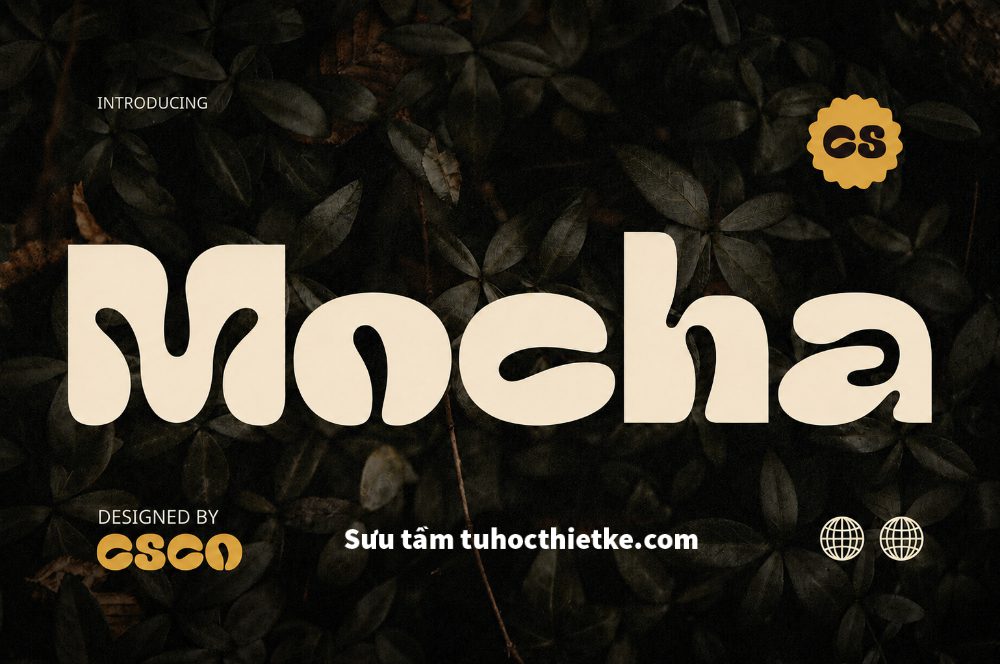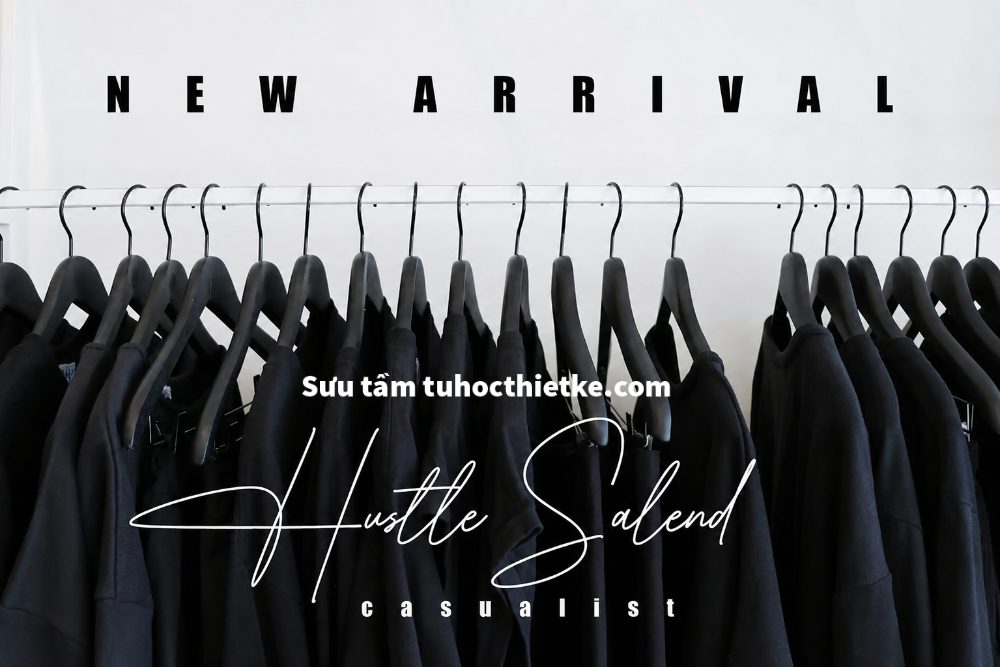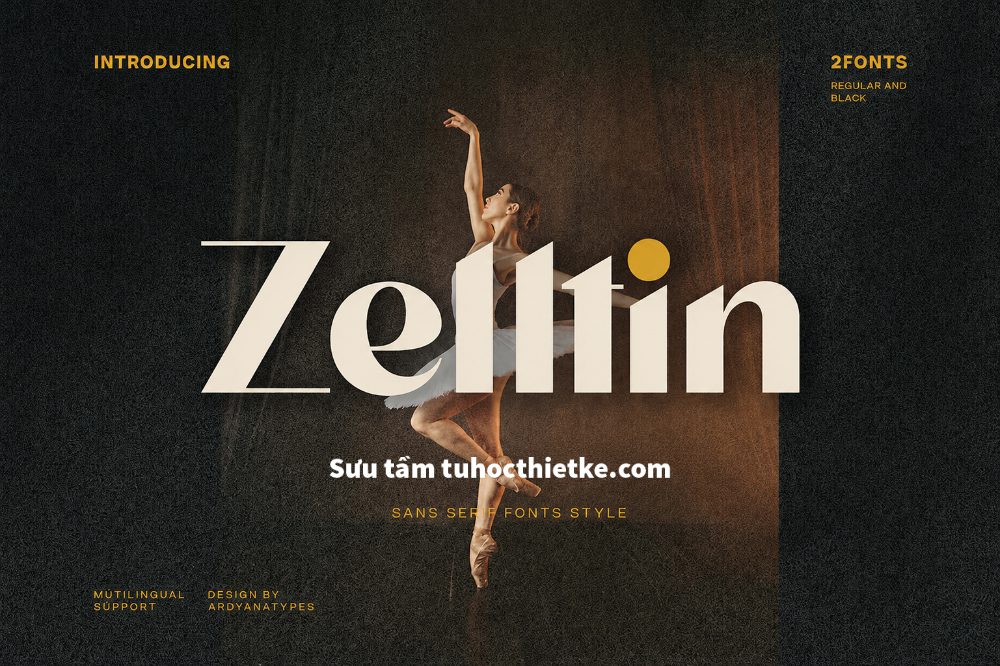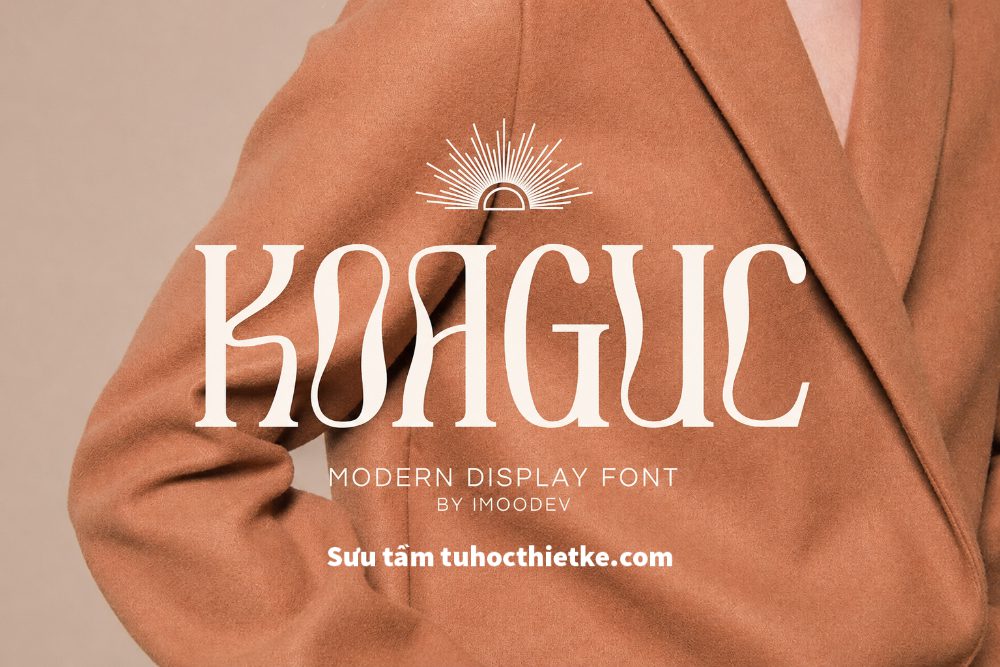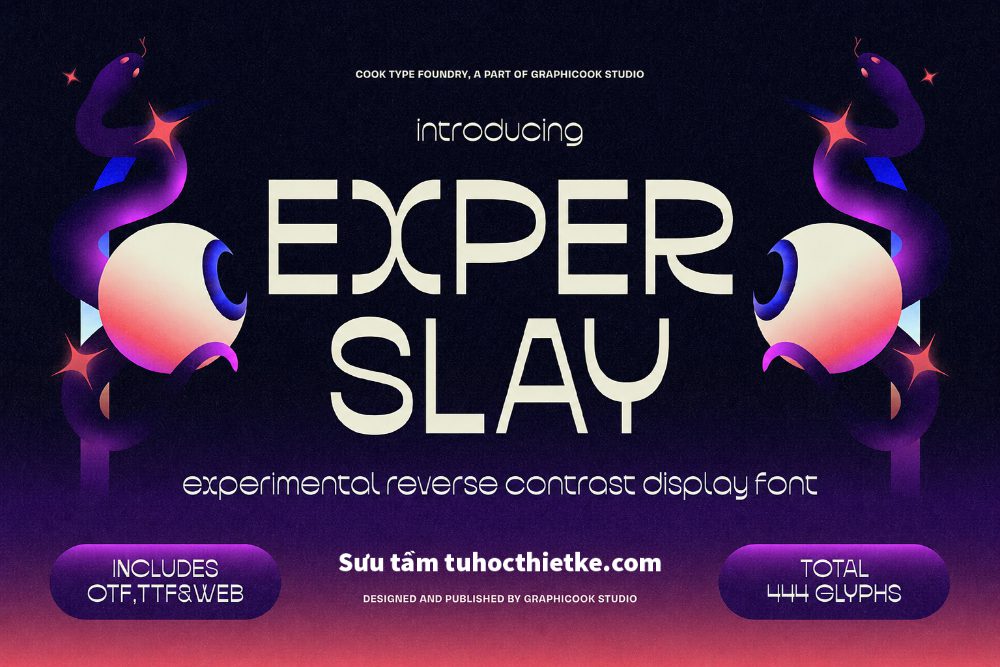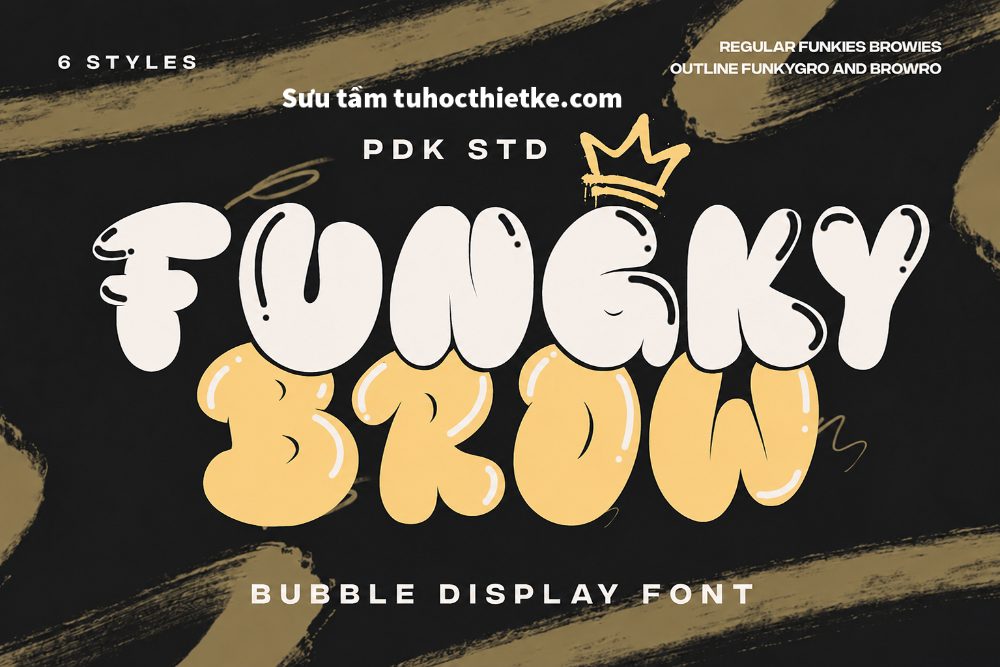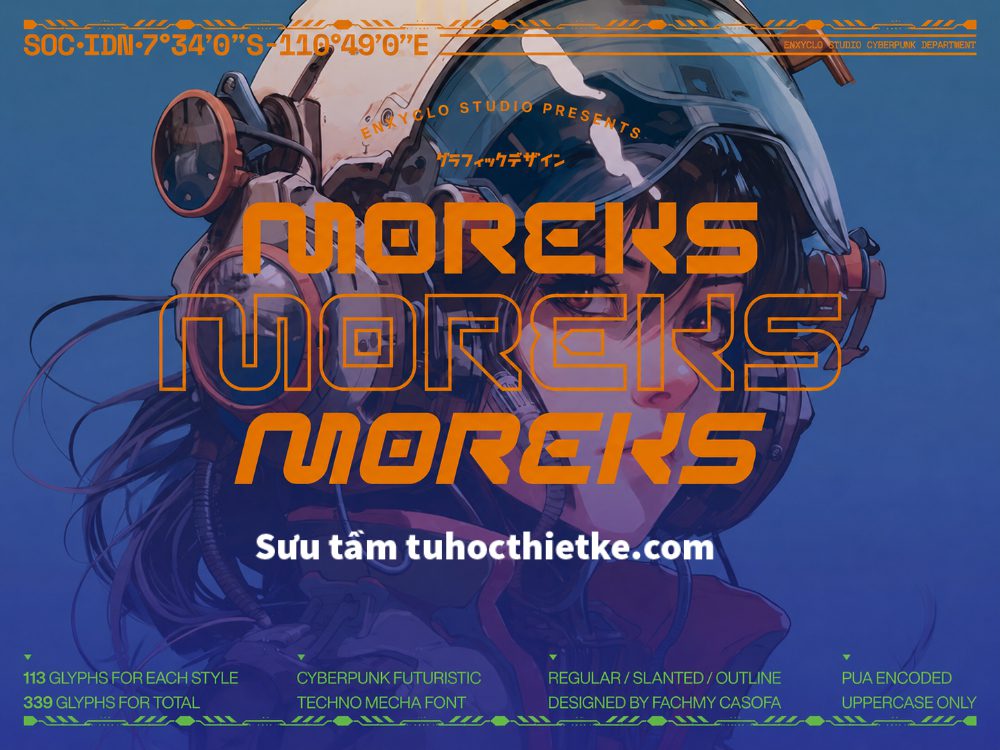
Font Chữ Miễn Phí 7 font cho dự án thiết kế là bộ tài nguyên hữu ích dành cho designer, content creator, freelancer và những ai thường xuyên làm việc với typography. Trong thiết kế đồ họa, font chữ không chỉ là công cụ hiển thị nội dung mà còn góp phần tạo nên phong cách, cảm xúc và độ chuyên nghiệp cho toàn bộ ấn phẩm. Một font chữ phù hợp có thể giúp poster nổi bật hơn, logo có cá tính hơn, banner dễ thu hút hơn và các dự án thương hiệu trở nên đồng bộ hơn.
Bộ 7 font chữ được chọn lọc trong chủ đề này hướng đến sự đa dạng, dễ ứng dụng và phù hợp với nhiều phong cách thiết kế khác nhau. Tuy nhiên, cần lưu ý rằng đây là font quốc tế, không phải Font Việt Hóa. Vì vậy, khi sử dụng cho nội dung tiếng Việt, bạn nên kiểm tra kỹ khả năng hỗ trợ dấu trước khi đưa vào dự án chính thức.
Vì Sao Designer Nên Sở Hữu Nhiều Font Chữ?
Font chữ là một trong những yếu tố quan trọng nhất trong thiết kế. Mỗi kiểu font đều mang một tinh thần riêng, có font hiện đại, có font cổ điển, có font tối giản, có font mạnh mẽ và cũng có font mềm mại, nghệ thuật. Khi có nhiều lựa chọn font trong thư viện cá nhân, designer sẽ dễ dàng thử nghiệm nhiều hướng thiết kế khác nhau mà không mất quá nhiều thời gian tìm kiếm.
Một bộ font được chọn lọc tốt sẽ giúp quá trình làm việc nhanh hơn. Thay vì phải tìm từng font riêng lẻ cho mỗi dự án, bạn có thể lưu sẵn những font phù hợp với các nhóm thiết kế phổ biến như logo, poster, social media, bao bì, thumbnail, portfolio hoặc banner quảng cáo. Đây là cách giúp tiết kiệm thời gian nhưng vẫn đảm bảo chất lượng thẩm mỹ.
Font Quốc Tế Có Phù Hợp Với Thiết Kế Không?
Phù hợp cho thiết kế tiếng Anh và chữ không dấu
Vì đây là font quốc tế, không phải Font Việt Hóa, các font này thường phù hợp nhất với những thiết kế sử dụng tiếng Anh, tên thương hiệu, chữ không dấu, slogan ngắn hoặc các dự án có nội dung typography đơn giản. Nếu bạn làm poster quốc tế, bìa album, thiết kế thời trang, logo cá nhân, banner sản phẩm hoặc artwork dùng chữ tiếng Anh, những font này có thể phát huy hiệu quả rất tốt.
Font quốc tế thường có nhiều phong cách độc đáo, từ tối giản, sang trọng đến phá cách, cá tính. Đây là lý do nhiều designer vẫn ưu tiên sử dụng font quốc tế trong các dự án cần tạo cảm giác hiện đại, thời trang hoặc khác biệt.
Cần kiểm tra kỹ khi dùng tiếng Việt
Điểm cần chú ý nhất khi dùng font quốc tế là khả năng hỗ trợ tiếng Việt. Một số font có thể hiển thị được chữ cái cơ bản nhưng thiếu dấu, lệch dấu hoặc lỗi ký tự khi gõ tiếng Việt. Điều này có thể làm thiết kế mất thẩm mỹ, đặc biệt nếu dùng cho tiêu đề lớn hoặc ấn phẩm in ấn.
Trước khi sử dụng Font Chữ Miễn Phí cho dự án tiếng Việt, bạn nên thử trước các câu có nhiều dấu như “Thiết kế sáng tạo”, “Dự án thương hiệu”, “Nội dung truyền thông” để kiểm tra độ ổn định. Nếu font không hỗ trợ dấu tốt, hãy dùng cho chữ không dấu hoặc chỉ áp dụng trong các phần tiếng Anh.
7 Font Chữ Có Chọn Lọc Phù Hợp Với Nhiều Dự Án
Font hiện đại cho thiết kế tối giản
Nhóm font hiện đại thường có đường nét gọn gàng, sạch sẽ và dễ đọc. Đây là lựa chọn phù hợp cho các thiết kế mang phong cách minimal, công nghệ, portfolio, website, profile cá nhân hoặc thương hiệu trẻ trung. Font hiện đại giúp bố cục trông chuyên nghiệp, rõ ràng và dễ tiếp cận người xem.
Khi sử dụng font hiện đại, bạn có thể kết hợp với nền trắng, màu trung tính, hình ảnh sản phẩm hoặc bố cục nhiều khoảng trống để tạo cảm giác tinh tế. Đây là kiểu font rất dễ ứng dụng trong nhiều dự án thiết kế khác nhau.
Font serif cho phong cách sang trọng
Font serif là nhóm font có chân, thường tạo cảm giác thanh lịch, cổ điển và cao cấp. Kiểu font này phù hợp với thiết kế logo, bao bì mỹ phẩm, thương hiệu thời trang, thiệp mời, bìa sách, tạp chí hoặc các sản phẩm cần sự tinh tế.
Nếu dự án của bạn hướng đến hình ảnh sang trọng, font serif có thể giúp nâng tầm tổng thể thiết kế. Tuy nhiên, nên dùng font serif với kích thước hợp lý để đảm bảo độ dễ đọc, đặc biệt khi áp dụng trên màn hình nhỏ hoặc thiết kế social media.
Font display cho tiêu đề nổi bật
Font display thường có cá tính mạnh, được thiết kế để tạo điểm nhấn thị giác. Đây là lựa chọn phù hợp cho poster, banner, thumbnail, bìa album, tiêu đề quảng cáo hoặc các ấn phẩm cần thu hút sự chú ý nhanh.
Với font display, bạn không nên dùng cho đoạn văn dài vì có thể gây khó đọc. Thay vào đó, hãy dùng cho tiêu đề chính, headline hoặc một vài dòng chữ ngắn. Khi kết hợp cùng font phụ đơn giản, thiết kế sẽ vừa nổi bật vừa cân bằng hơn.
Font viết tay cho thiết kế sáng tạo
Font viết tay mang lại cảm giác tự nhiên, gần gũi và giàu cảm xúc. Kiểu font này phù hợp với các dự án về handmade, thời trang, lifestyle, thiệp, quote, poster nghệ thuật hoặc social media cá nhân.
Font viết tay thường tạo cảm giác mềm mại và cá tính, nhưng cần chọn loại có độ rõ ràng tốt. Nếu nét chữ quá phức tạp, người xem có thể khó đọc, nhất là khi thiết kế dùng trên ảnh nền nhiều chi tiết.
Ứng Dụng Font Chữ Trong Các Dự Án Thiết Kế
Tuy nhiên, vì đây là font quốc tế, không phải Font Việt Hóa, bạn nên kiểm tra kỹ khả năng hỗ trợ tiếng Việt trước khi sử dụng. Khi chọn đúng font, phối hợp hợp lý và dùng đúng mục đích, thiết kế của bạn sẽ trở nên nổi bật, chuyên nghiệp và truyền tải cảm xúc tốt hơn.